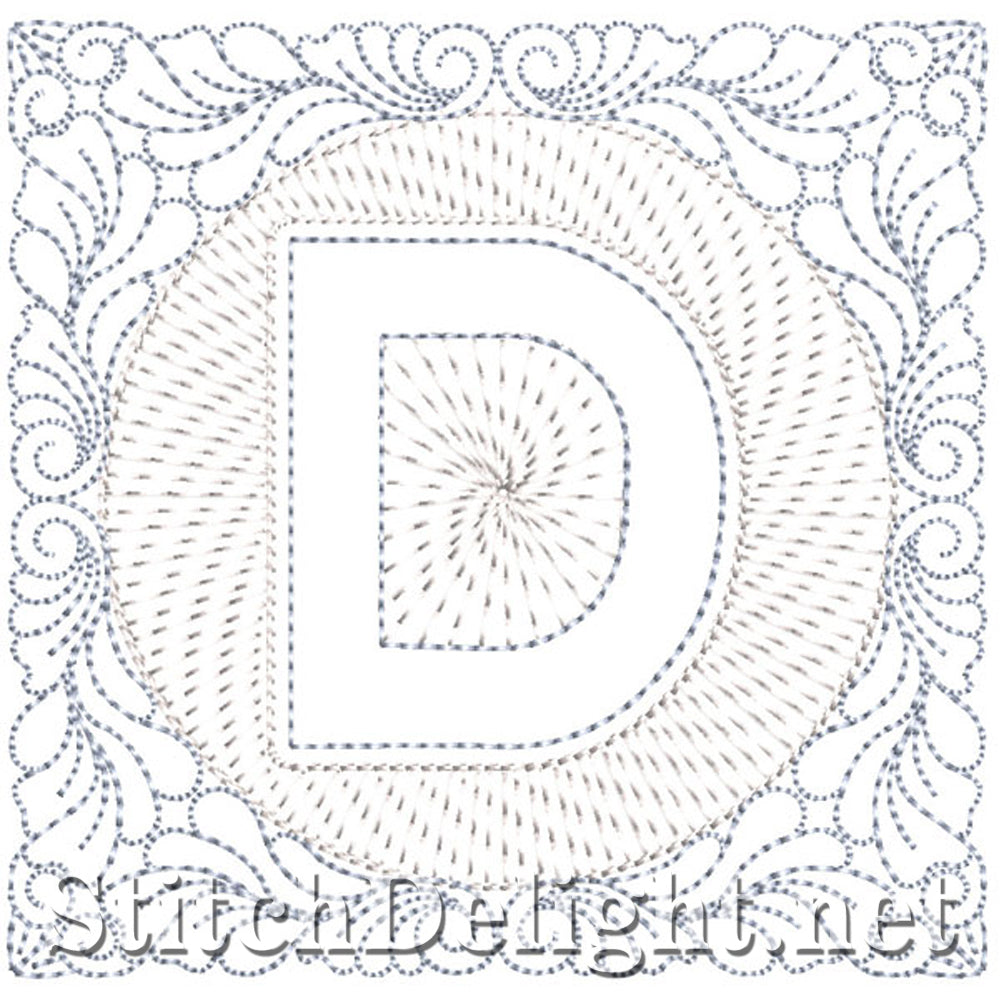
SDS1185 Quilters Blockschrift D
Diese schöne Schrift sieht umwerfend aus, wenn sie auf ein Sandwich aus Cutaway, Watte und Stoff genäht wird - Stretchgewebe ergibt einen atemberaubenden hohen Loft - buchstabieren Sie einen Namen oder machen Sie einen Alphabet-Quilt - Diese werden im 4x4-Hoop gemacht (Sie können vergrößern .) nach Belieben) Blockgröße ist 3,74 x 3,74" und Stichzahl mehr oder weniger 6600 Stiche